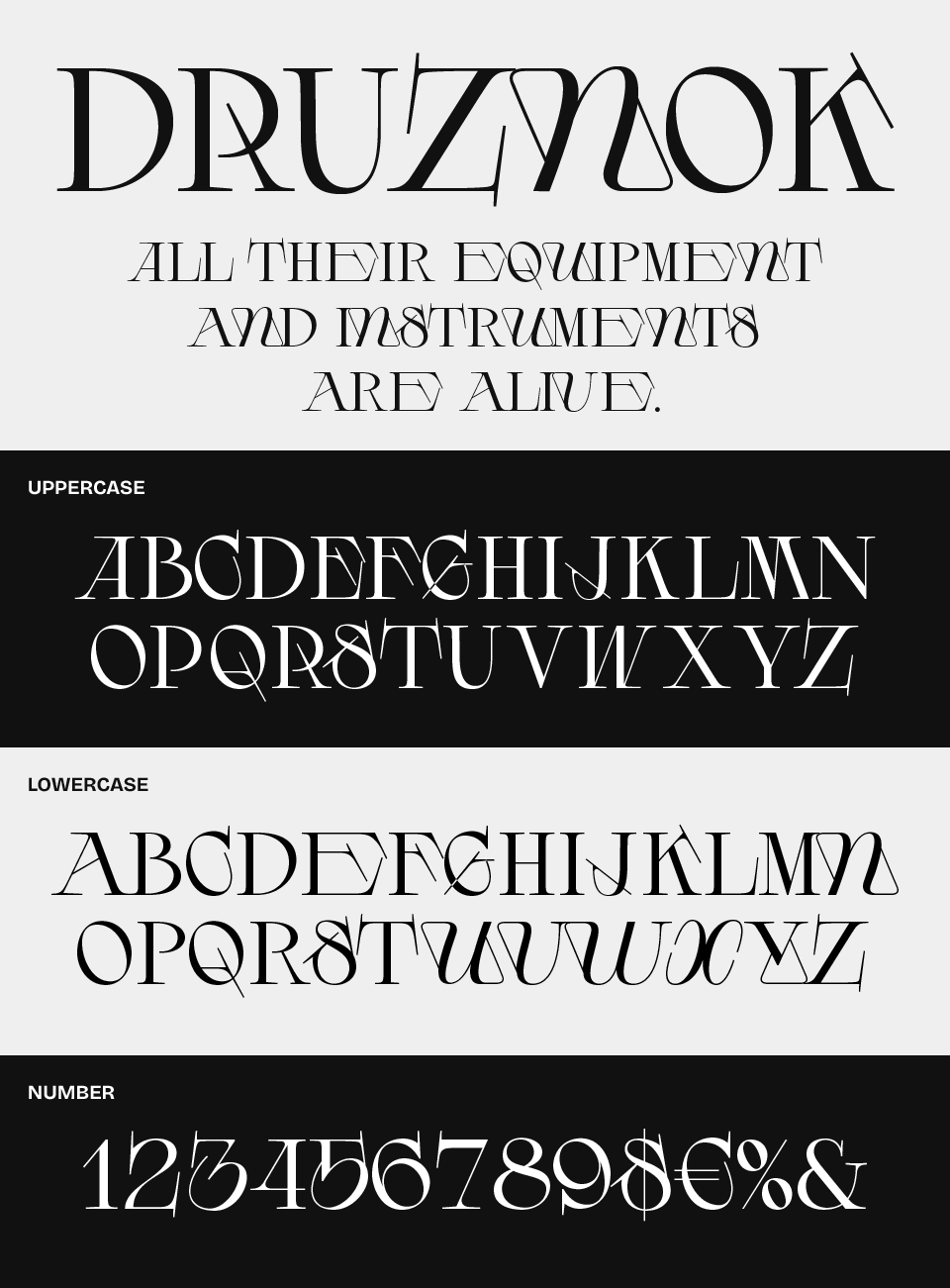
DRUZHOKフォントは、クラシックな書体にクセを強めな遊び心のあるひねりを加えたようなデザインが特徴的なフォントです。
オシャレでもあり、カッコよくもある細くエレガントな骨格を保ちつつ、アルファベットごとに異なる個性が際立ち、視線を惹きつけます。斜めに切り替わるセリフや、文字の一部が欠けたような変則的な形状が、モダンでユニークなアクセントを生んでいます。
アート性の高いタイポグラフィを求める場面にぴったりで、ファッション誌やポスター、ブランドロゴなどに使えば、印象的で前衛的な表現ができます。